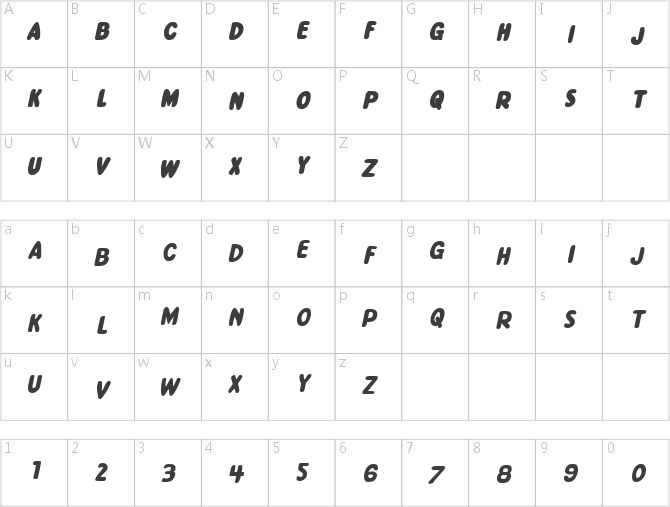
Excelsior-Comics-Expanded-Italic 详情页
Excelsior-Comics-Expanded-Italic
Excelsior-Comics-Expanded-Italic字体字库是一款让人赏心悦目、百看不厌的英文字体,适合各类广告和产品包装设计应用,字体大小0.05MB,格式为ttf字体,上传用户是82年的拉菲,作者/版权方为未知